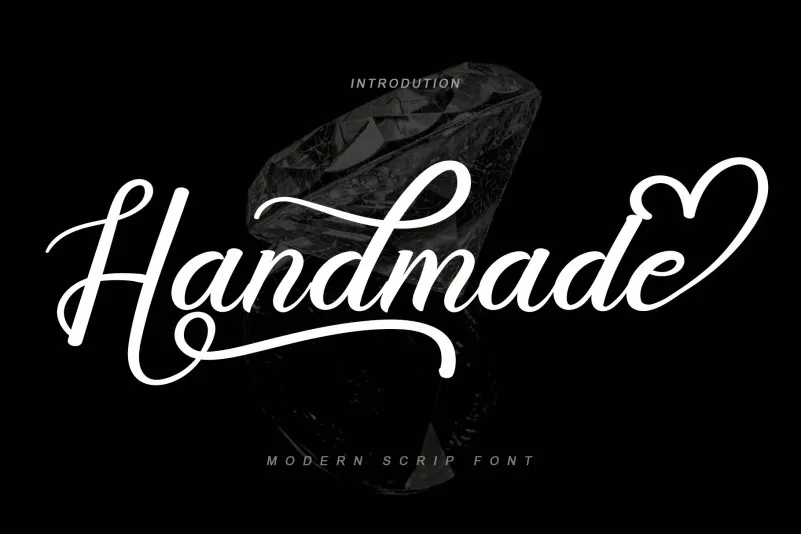
Esta é uma fonte de calligrafia romântica e doce, onde os caracteres dançam ao longo da linha base. Ela traz um toque sofisticado a qualquer projeto gráfico que você deseje criar! Essa fonte possui PUA encoded, o que permite que você facilmente acesse todos os seus incríveis símbolos e ligaduras. A descrição original em inglês foi muito útil para entender as qualidades únicas desta fonte. Ela não apenas oferece um toque de elegância e sofisticação, mas também traz uma atmosfera romântica que se adapta perfeitamente a projetos relacionados à decoração e artesanato. O facto de ter ligaduras (ligatures) adicionadas à fonte eleva ainda mais o seu valor para designers que procuram um detalhe único para seus trabalhos gráficos. A fonte “Handmade Font” criada pela designer kateengciu é uma excelente escolha para quem está em busca de algo romântico, sofisticado e versátil. Ela faz do seu design um momento especial, tornando os projetos mais atraentes e encantadores. Como uma fonte script, é perfeitamente adaptável a várias aplicações: desde rótulos personalizados até criação de materiais para decoração casada. Engane-se se pensa que esta font é somente uma opção de design moderna – ela traz um toque nostálgico e delicado que torna qualquer projeto único e especial.